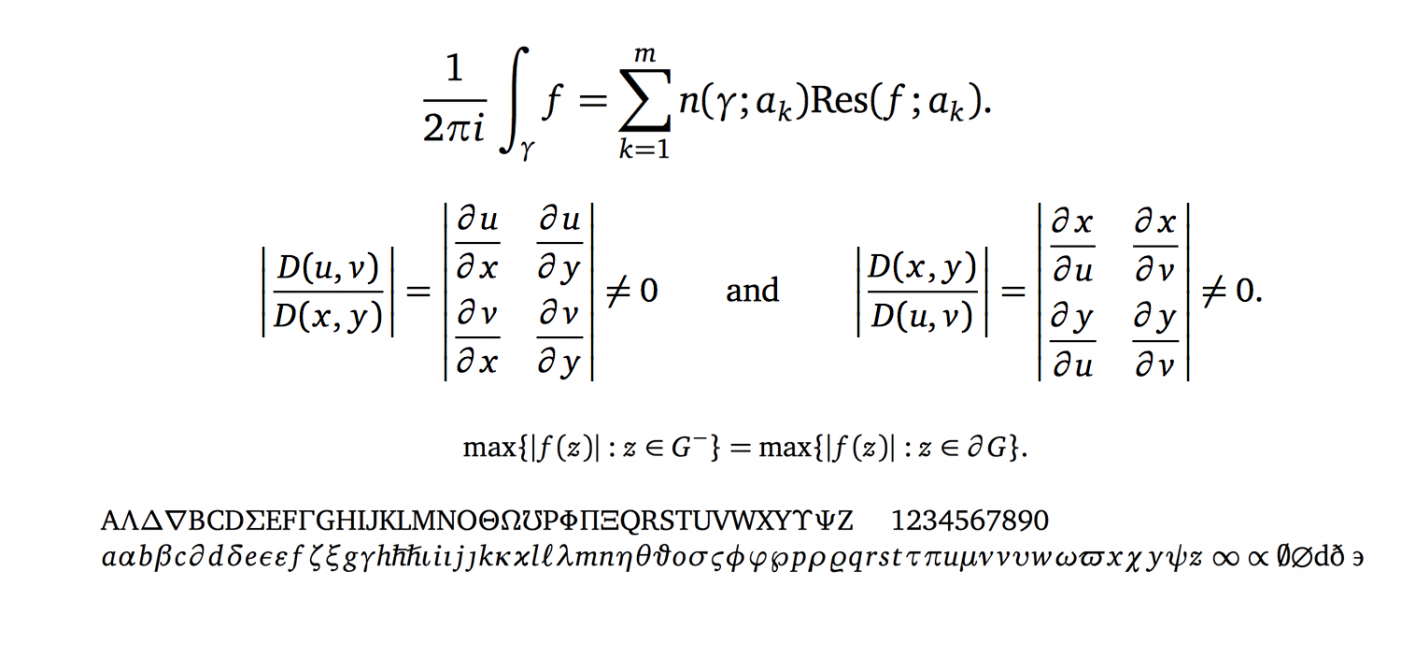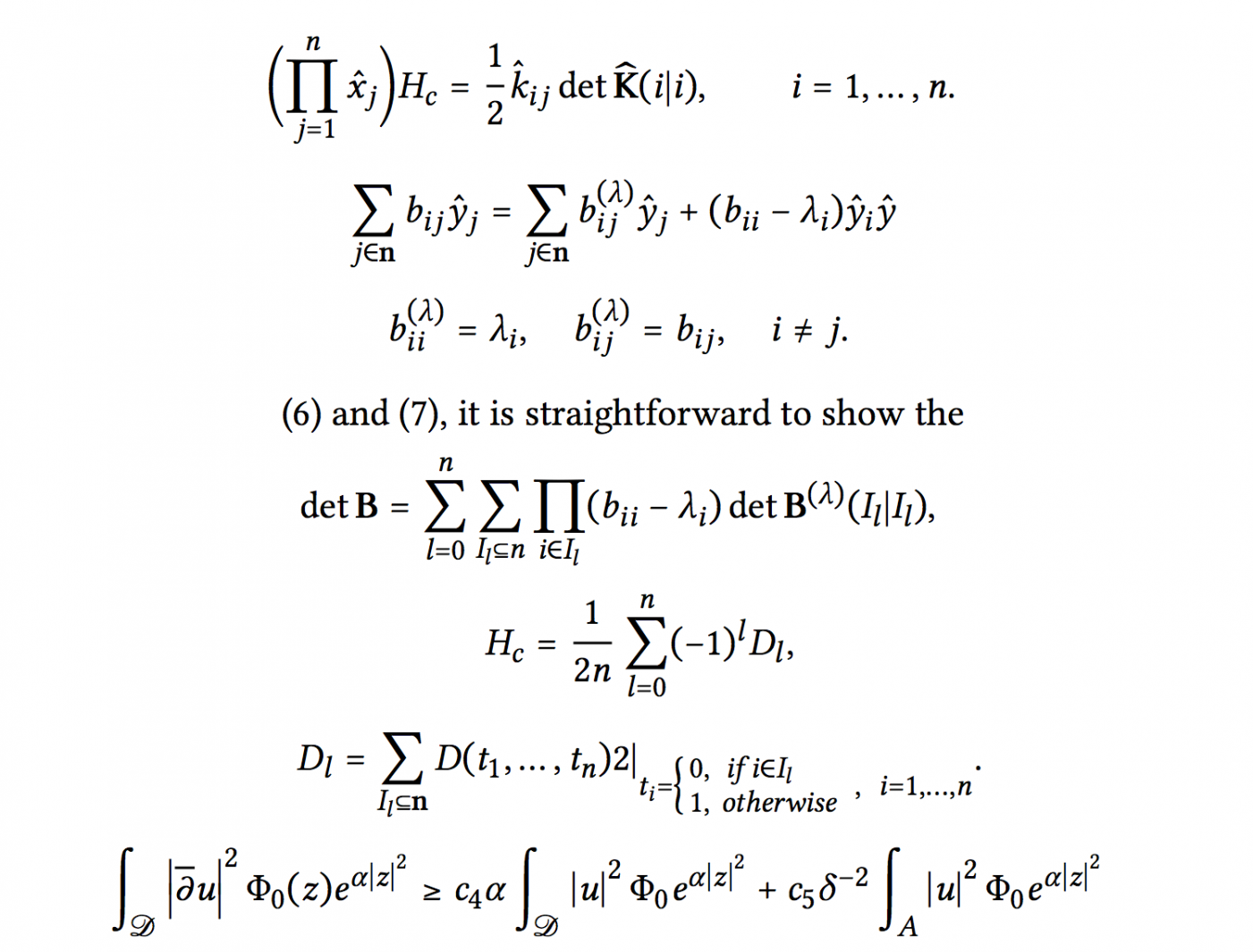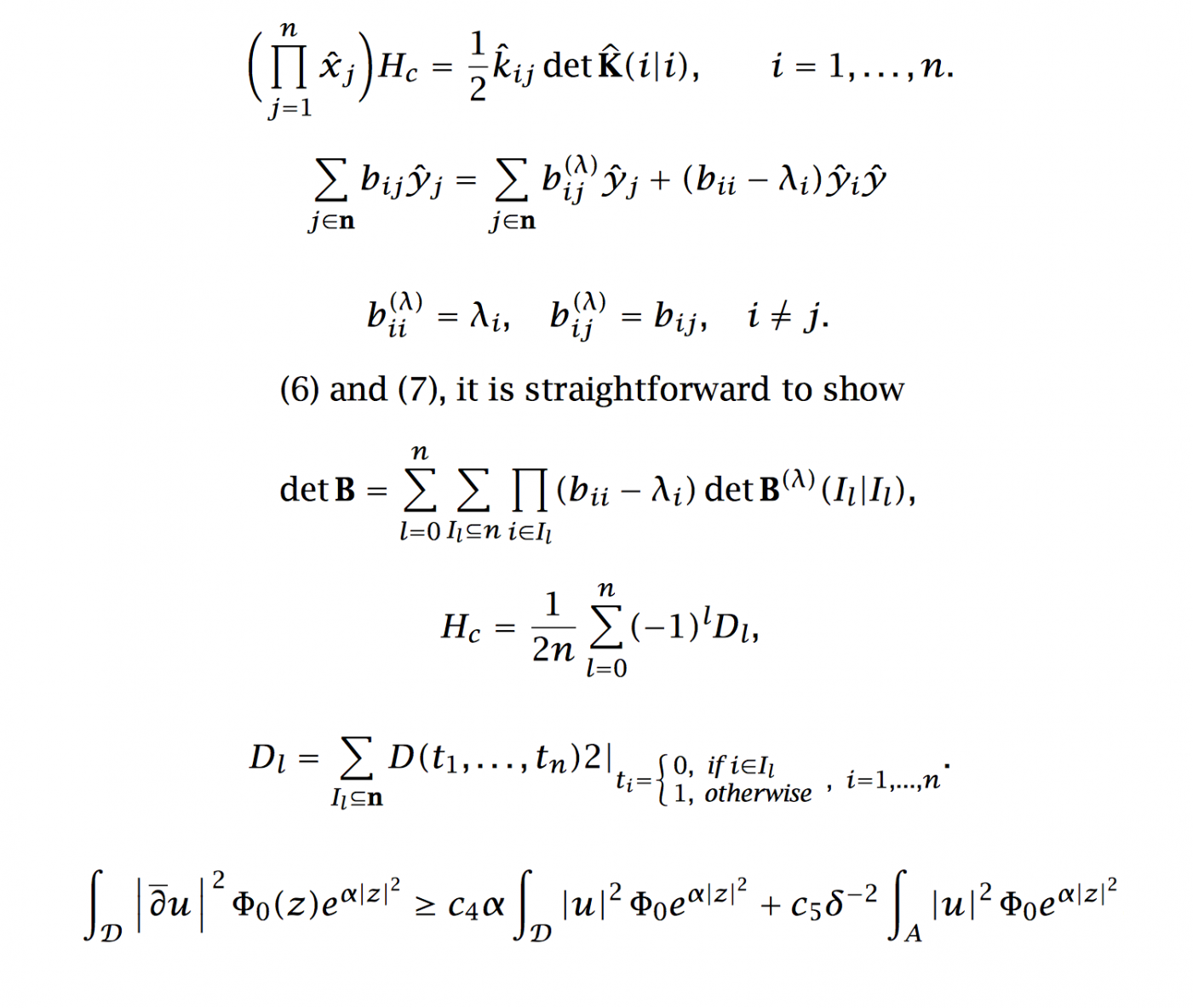
[Mitglied o.o…] Geschrieben März 5, 2018 Teilen Geschrieben März 5, 2018 Hallo! Ich möchte für eine naturwissenschaftliche Arbeit (inkl. viel Mathe und Chemie) gerne die Schrift Skolar Serif als Brotschrift und Skolar Sans für Überschriften etc. nutzen. Die Arbeit wird mit LaTeX (LuaLaTeX) geschrieben. Nun bin ich auf der Suche nach einer passenden Mathematik-Schrift. Da ich mich leider mit Typographie nicht auskenne, wäre es sehr schön, wenn mir hier ein Profi ein paar Tipps geben könnte. Daneben stellt sich mir noch die Frage, was ich denn mindestens kaufen muss, damit alle normalen Anwendungen abgedeckt sind: Normal, Italic, Bold und Bold-Italic für Serif und Sans müsste doch ausreichen oder? Benötige ich dann die normale oder die PE-Version (besonders wegen den griechischen Buchstaben)? Braucht man noch etwas, besonders im Hinblick auf die LaTeX Verwendung? Vielen Dank! o.o Link zu diesem Kommentar
[Mitglied caf2…] Geschrieben März 6, 2018 Teilen Geschrieben März 6, 2018 Hier wurden Schriften für den Mathe-Satz schon mal behandelt, vielleicht hilft dir das schon weiter: Link zu diesem Kommentar
[Mitglied o.o…] Geschrieben März 6, 2018 Themen-Ersteller Teilen Geschrieben März 6, 2018 Danke, allerdings zielte meine Frage eher darauf ab, welche Mathe-Schrift typographisch zu den Skolar-Schriften passt. Link zu diesem Kommentar
[Mitglied Kath…] Geschrieben März 8, 2018 Teilen Geschrieben März 8, 2018 ich vermute, dass unser Kollege TobiW gerade offline zu viel um die Ohren hat, um hier regelmäßig mitzulesen. Ich hoffe, er entdeckt Deine Anfrage noch – er hat nämlich sowohl Ahnung von Mathe, als auch von LaTeX und Typografie. Er hat bestimmt einen Tipp für Dich! 1 Link zu diesem Kommentar
Ralf Herrmann Geschrieben März 8, 2018 Teilen Geschrieben März 8, 2018 Man kann ihn ja mal vorsichtig herbeirufen: @TobiW 1 2 Link zu diesem Kommentar
[Mitglied CRud…] Geschrieben März 9, 2018 Teilen Geschrieben März 9, 2018 Um noch geschwind die Nebenfrage zu beantworten: Bei der Skolar brauchst Du in der Tat die PE-Version sofern Du auf griechische Buchstaben angewiesen bist. Und was die Schnitte angehen: das hängt ja von Deinem Layout ab. Regular und Italics natürlich auf alle Fälle. Wird sie auch für Überschriften eingesetzt dann entweder Semibold, ggf. mit passender Italics-Variante (gibt es die überhaupt?) oder eben Bold. Wenn Du aber tatsächlich die Skolar Sans einsetzt dann mußt Du Dir überlegen ob halbfette oder fette Auszeichnungen im Text vorkommen. Das kann man auch schnell mal übersehen: oftmals wird in Fachjournalen in den Bildlegenden Figure 1: … halbfett oder fett gesetzt. Bei meiner Dissertation bin ich im Fließtext mit Regular und Italics ausgekommen. Wobei: die sind natürlich qualitativ schon sehr hochwertig. Wenn Du es Dir leisten kannst und von beiden ein Paket mit jeweils vier Schnitten kaufst dann hast Du auch erstmal ein paar Jahre Ruhe. Mathe-Satz: da habe ich leider zu wenig Erfahrung, von daher kann ich nix beisteuern. Beste Grüße, Christian 1 Link zu diesem Kommentar
[Mitglied o.o…] Geschrieben März 9, 2018 Themen-Ersteller Teilen Geschrieben März 9, 2018 Danke für die Rückmeldungen! Ich habe bisher drei Möglichkeiten gefunden (mit ausgebautem Mathematik-Teil), willkürliche Reihenfolge: 1. Lucida Math (https://www.tug.org/store/lucida/) 2. Libertinus Math (https://github.com/khaledhosny/libertinus) 3. Charter (\mathdesign package) In welcher Reihenfolge würden die denn typographisch am besten zur Skolar passen? Danke! Link zu diesem Kommentar
[Mitglied R::b…] Geschrieben März 9, 2018 Teilen Geschrieben März 9, 2018 vor 31 Minuten schrieb o.o: In welcher Reihenfolge würden die denn typographisch am besten zur Skolar passen? Find ich gut, dass Du uns eine Vorauswahl rausgesucht hast. Wenn Du jetzt noch je ein Schriftmuster ergänzt, flattern die gewünschten Rückmeldungen sicher wie von alleine rein. Link zu diesem Kommentar
[Mitglied o.o…] Geschrieben März 9, 2018 Themen-Ersteller Teilen Geschrieben März 9, 2018 Naja, bei den Links findet man ja Schriftmuster. Aber hier nochmal direkte Links, es geht dabei nur um den Formel-Font: Lucida Math: https://www.tug.org/store/lucida/lucida-amsmath.pdf Libertinus Math: https://github.com/khaledhosny/libertinus/blob/master/documentation/libertinus-testmath.pdf Charter: https://mirror.informatik.hs-fulda.de/tex-archive/fonts/mathdesign/MD-Bitstream-Charter-example.pdf sollte typographisch hierzu passen: https://www.rosettatype.com/microsite/current/Skolar/files/Skolar_specimen.pdf Link zu diesem Kommentar
[Mitglied R::b…] Geschrieben März 9, 2018 Teilen Geschrieben März 9, 2018 Gemeint war eine aussagekräftige Abbildung des Schriftbildes. Link zu diesem Kommentar
[Mitglied o.o…] Geschrieben März 9, 2018 Themen-Ersteller Teilen Geschrieben März 9, 2018 Noch aussagekräftiger?!? Was anderes habe ich leider nicht. In den verlinkten Dokumenten sind doch die jeweiligen Fonts ausgiebig genutzt. Ich kann leider keinen direkten Vergleich mit der Skolar und den anderen Schriften basteln, da ich die Kommerziellen noch gar nicht habe. Gekauft wird erst, wenn fest steht, was ich denn kaufe ;) Link zu diesem Kommentar
[Mitglied Kath…] Geschrieben März 9, 2018 Teilen Geschrieben März 9, 2018 In Deine Antwort eingebundene Beispielbilder sind gemeint. Wenn Du auf „Antworten“ klickst, dann kannst Du über den Button „MyFonts-Schriftmuster“ jede gewünschte Schrift als Schriftmusterbild einbinden, die es bei MyFonts zu kaufen gibt. Schriften, die es dort nicht gibt, können als Screenshot der jeweiligen Schrift ebenfalls hochgeladen und in Deiner Antwort als Bild angezeigt werden. So zum Beispiel: Auf diese Weise erhöhst Du die Chance auf Antworten sehr, weil nicht jeder Betrachter die Zeit (und womöglich die Lust) hat, sich erst durch diverse Seite zu klicken, um Dir helfen zu können. 2 Link zu diesem Kommentar
[Mitglied o.o…] Geschrieben März 9, 2018 Themen-Ersteller Teilen Geschrieben März 9, 2018 Achso... leider habe ich nicht die gleichen Formeln für die Charter gefunden. Daher weicht das Beispiel im Inhalt ab. Skolar: Charter: Libertinus Math: Lucida Math: 1 Link zu diesem Kommentar
[Mitglied Þors…] Geschrieben März 10, 2018 Teilen Geschrieben März 10, 2018 vor 20 Stunden schrieb o.o: Ok, aber warum wird gerade dies dann so oft empfohlen? Weil die Empfehlenden i.a.R. STEM-Wissenschaftler sind und sich Typografie bestenfalls autodidaktisch so’n bisschen nebenbei angeeignet haben. In diesem Forum erhältst du hingegen Rat von Typografie-Profis. 1 Link zu diesem Kommentar